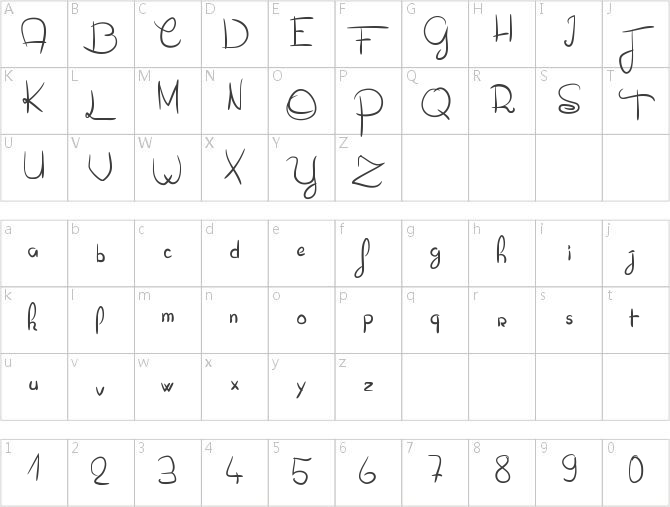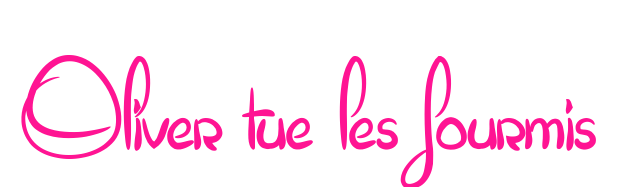
Oliver-tue-les-fourmis 詳情頁
字體名稱: Oliver-
Oliver-tue-les-fourmis
Oliver-tue-les-fourmis字體字庫是一款讓人賞心悅目、百看不厭的英文字體,適合各類廣告和產品包裝設計應用,字體大小0.04MB,格式為ttf字體,上傳用戶是1733150348,作者/版權方為未知